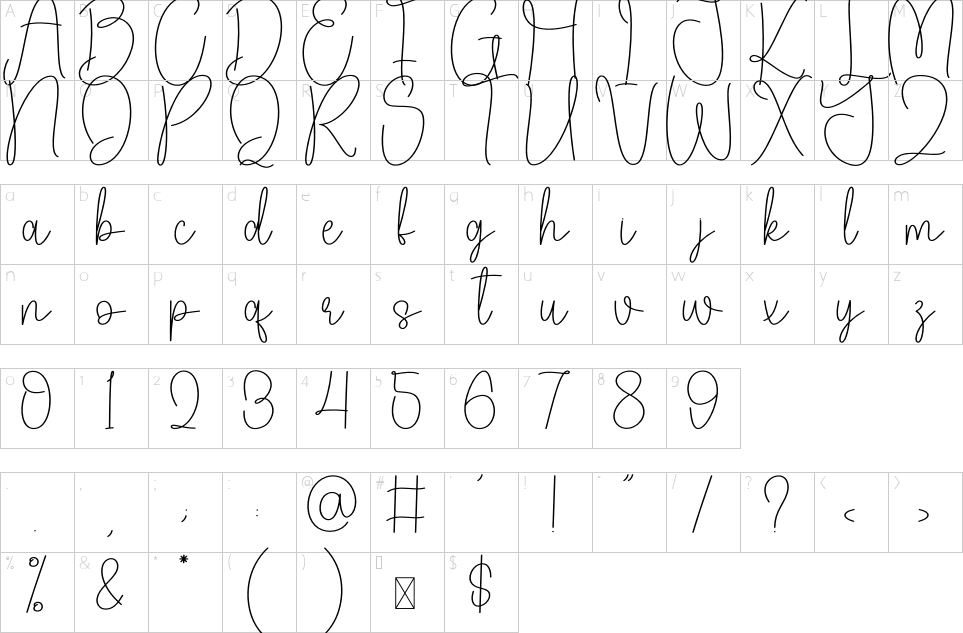
A fonte Justice é um recurso gráfico gratuito disponível para Windows e Mac. Desenhada por William Jhordy, esta fonte já foi baixada 254 vezes. Ela combina um estilo elegante e contemporâneo que pode ser usado em uma variedade de aplicações, desde rótulos e anúncios até criação de artigos e design gráfico. Se você está procurando por uma fonte moderna e versátil, Justice pode ser a escolha certa para seu projeto. Com seu design limpo e fácil de ler, é perfeita para personalizar qualquer tipo de documento ou arte digital. Baixe Justice agora e experimente o estilo único desta fonte.